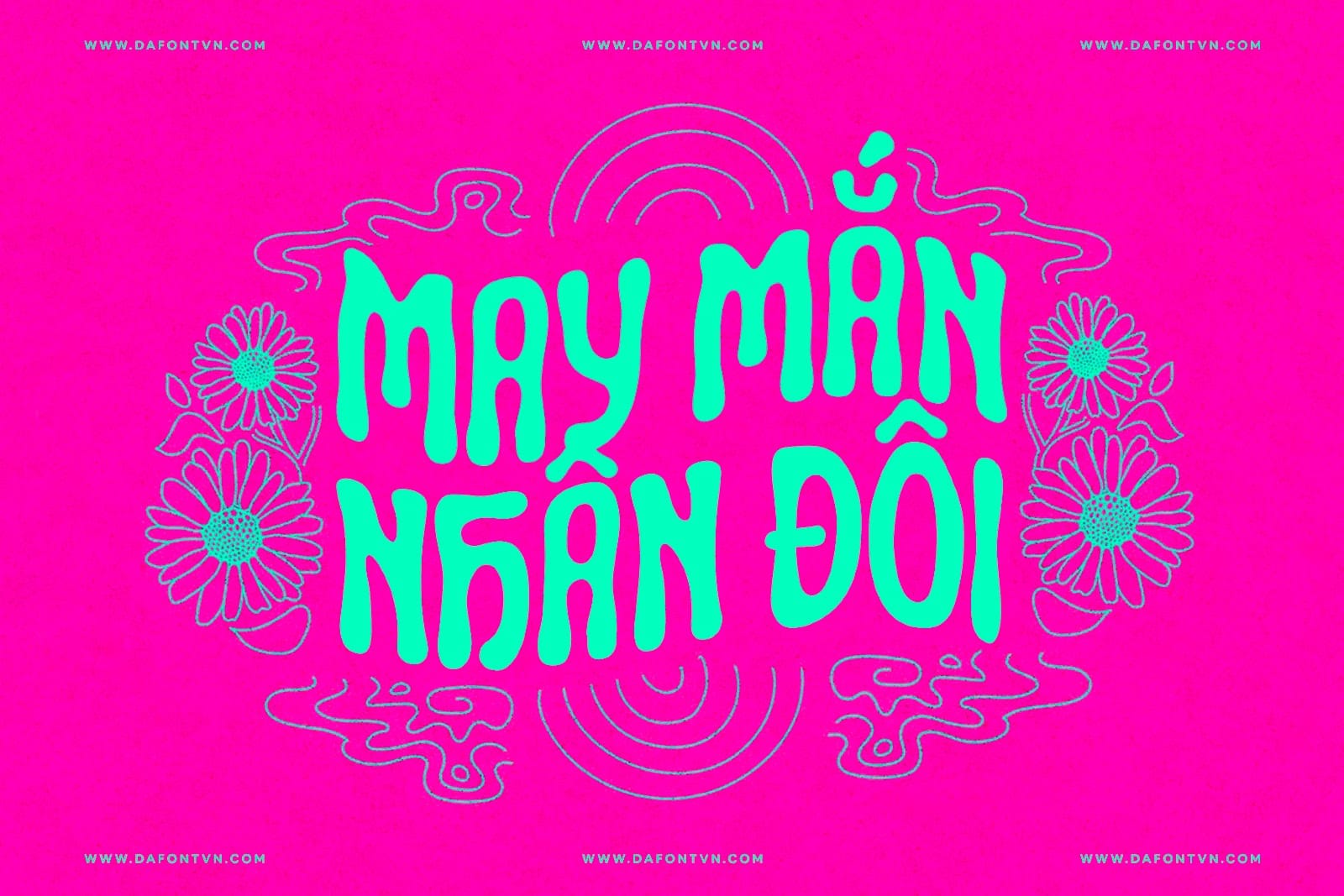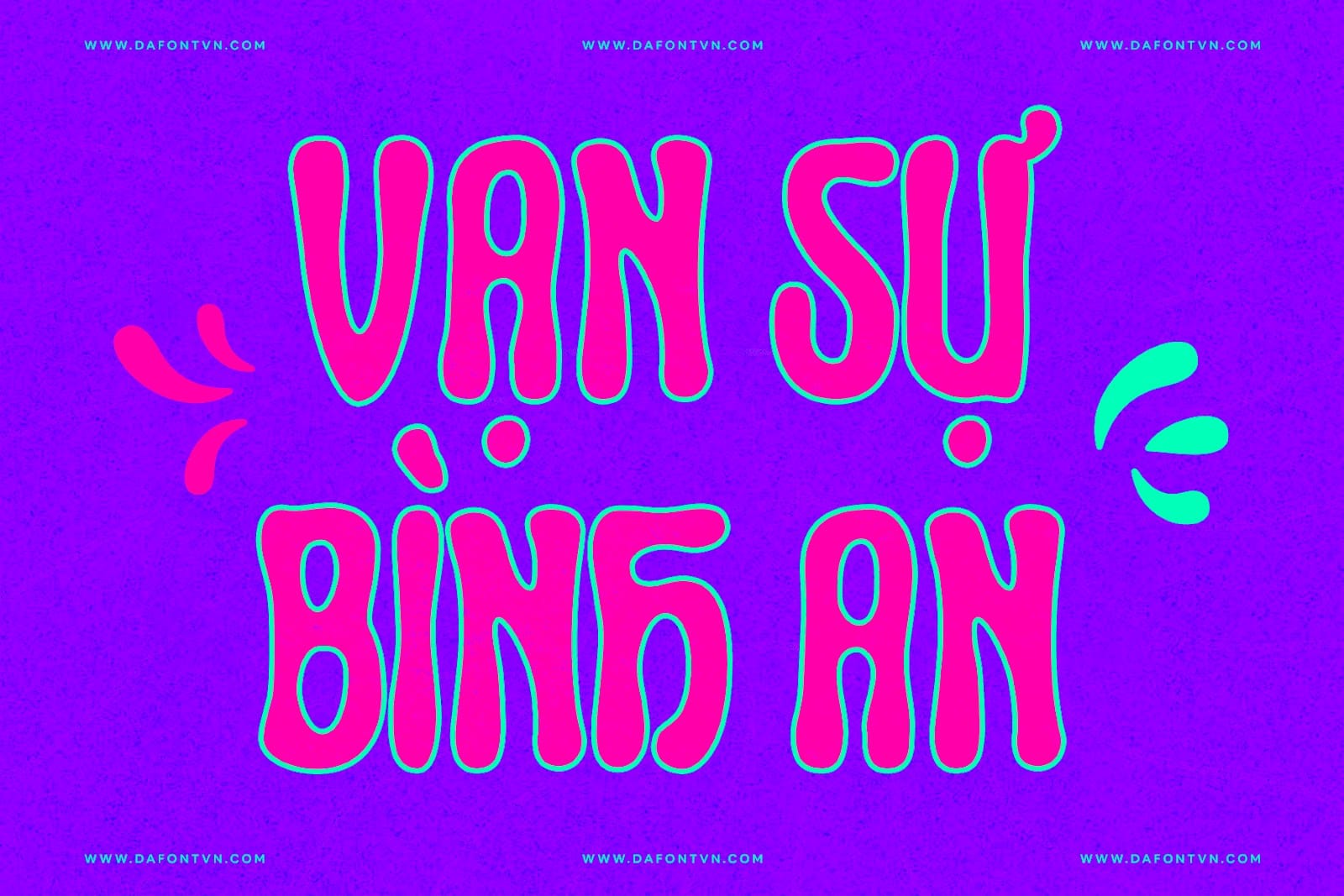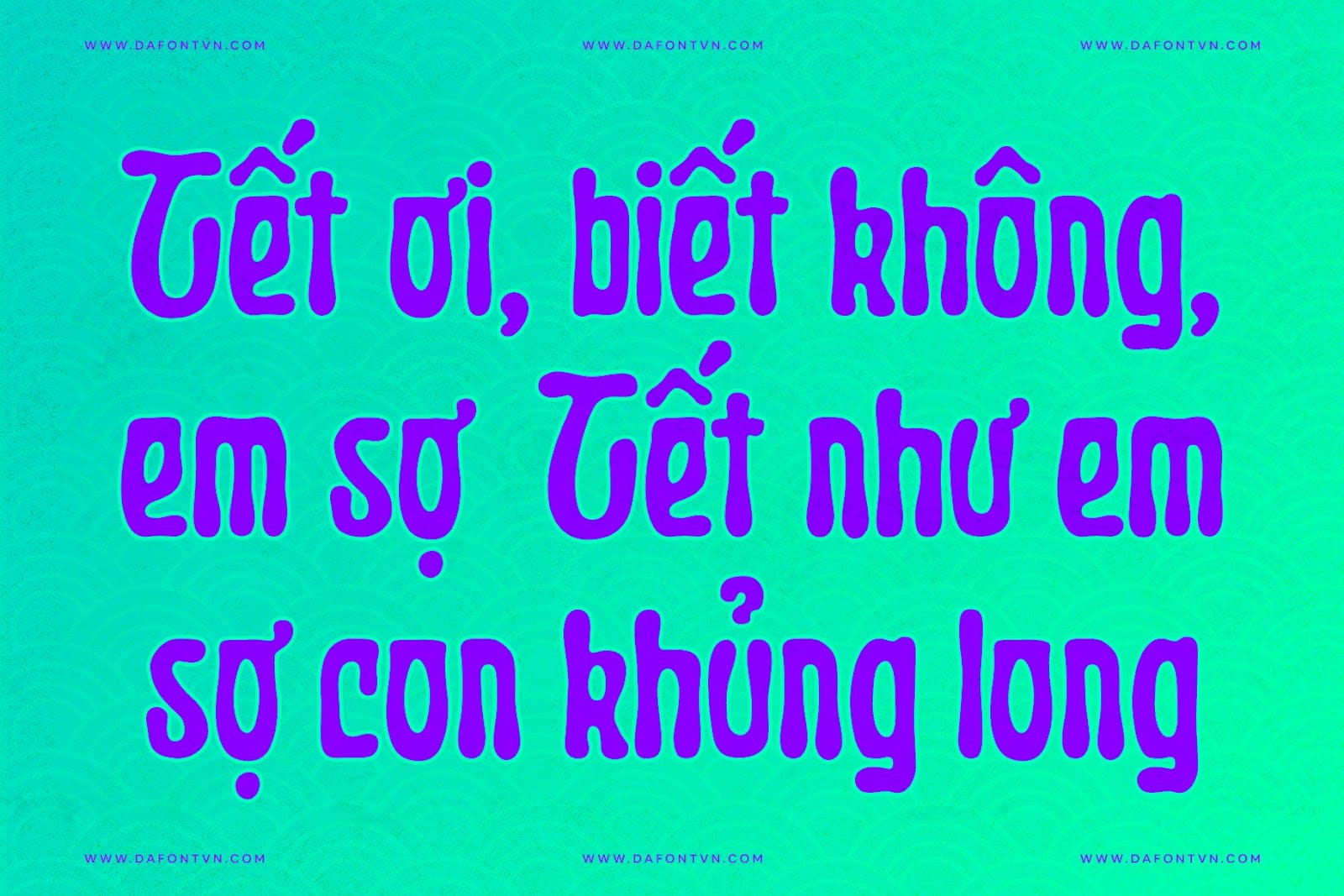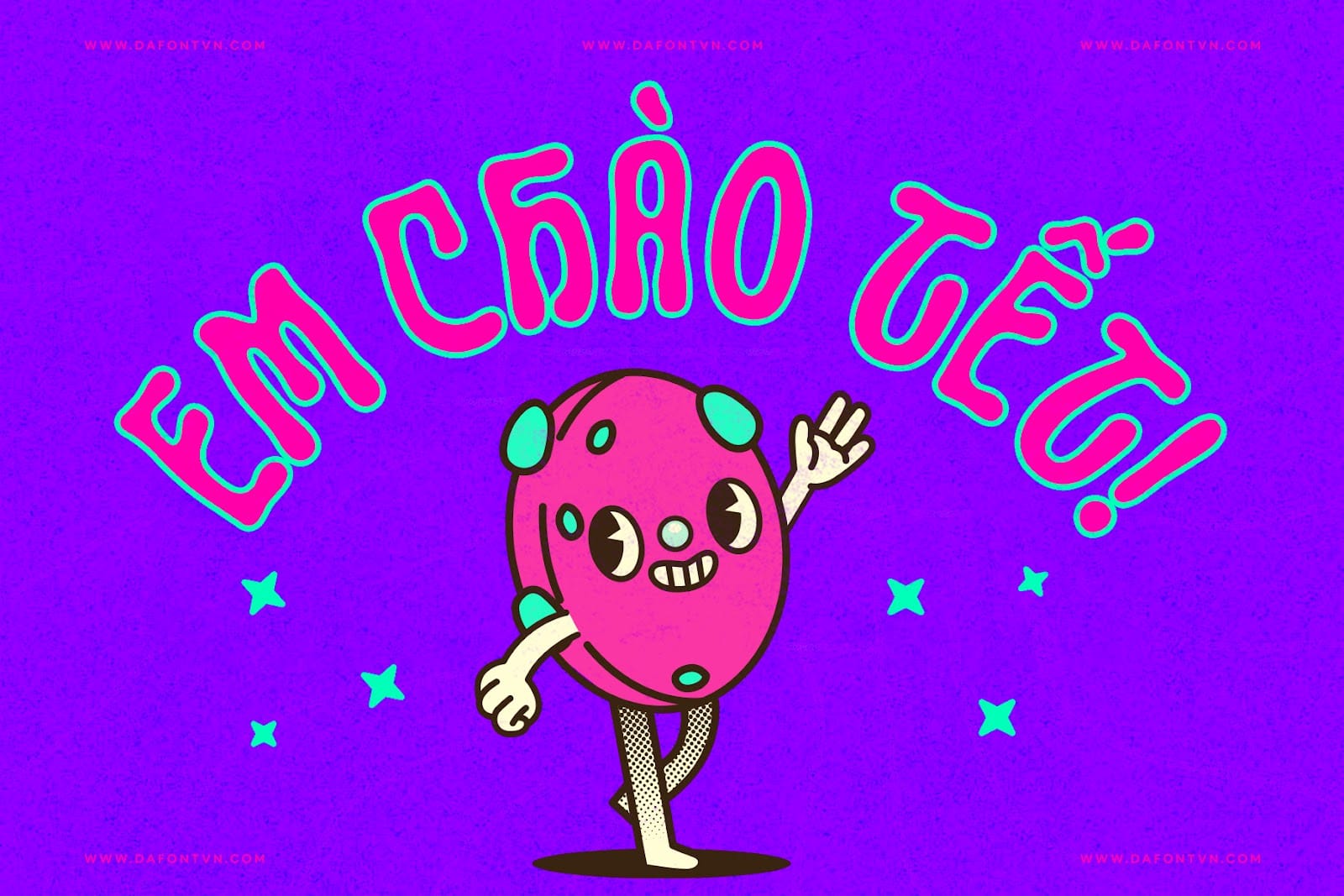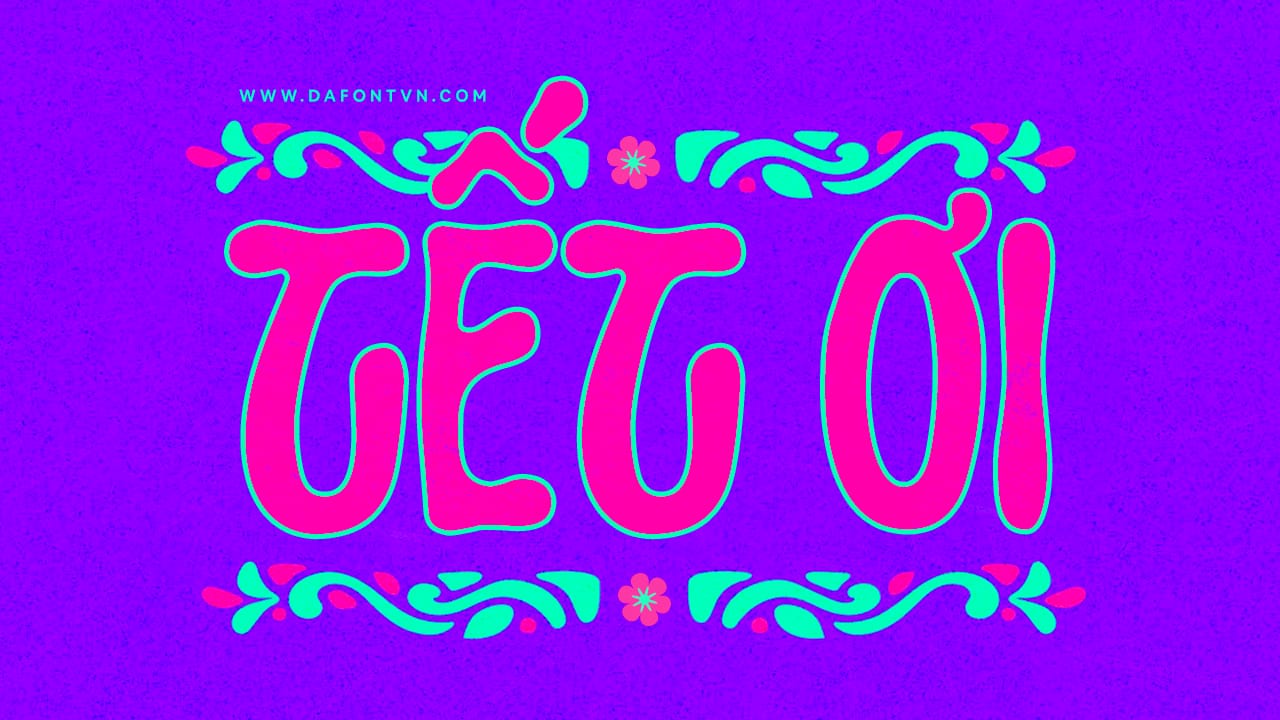
Lucidity là một kiểu font retro cực đẹp. Với phong cách pcychedelia kết hợp với nét hiện đại. Bạn có thể sử dụng font chữ này cho các dịp lễ như Tết, Trung Thu, Giáng Sinh…
Lucidity phù hợp dành cho thiết kế logo, tiêu đề, thương hiệu, tạp chí, bìa album, bìa sách, phim, thiết kế trang phục, thiệp mời, tờ rơi, áp phích, thiệp chúc mừng, bao bì sản phẩm hoặc bất kỳ thiết kế nào khác đòi hỏi một kiểu chữ mềm mại, hiện đại và đẹp mắt.
Font Lucidity được việt hóa rất tỉ mỉ, chỉn chu, tối ưu cũng như căn chỉnh lại các dấu và ký tự để hiển thị tốt hơn.